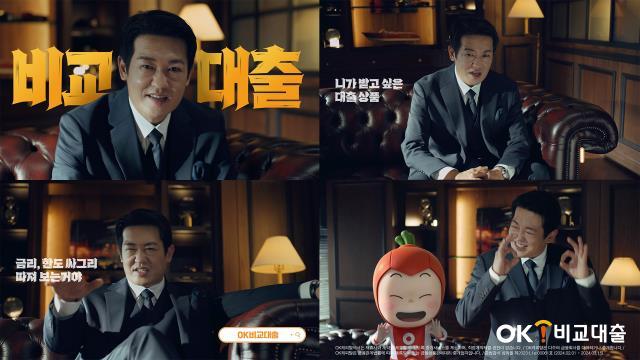
읏맨체 — OK금융그룹에서 배포하는 무료 폰트입니다. 어렵고 딱딱한 금융의 이미지를 친근하게 바꾸려 거칠고 강한 획으로 그린 장식용 서체
OK금융그룹이 2022년 세종대왕 탄신 625주년에 맞춰 공개한 서체입니다. 타이포 브랜딩 스튜디오 엉뚱상상과 함께 만들었고 그해 레드닷 어워드 본상을 받았습니다. 기획 의도가 분명합니다. 어렵고 딱딱할 것 같은 금융의 이미지를 친근하고 유머러스하게 바꾸려는 것이었습니다.
구성이 특이합니다. 굵기가 아니라 성격이 다른 세 서체로 나뉩니다. 읏찬체는 이글이글한 힘찬 기운이, 읏궁체는 장난기를 빼고 섬세함을 담은 진지함이, 읏뚱체는 둥글둥글 모난 곳 없는 엉뚱함이 특징이라고 설명합니다. 모티브는 그룹의 대표 캐릭터 읏맨이고, 읏맨 캐릭터 그림문자 열다섯 종이 자음과 모음 자리에 숨어 있어 타이핑하다 보면 뜬금없이 나타납니다.